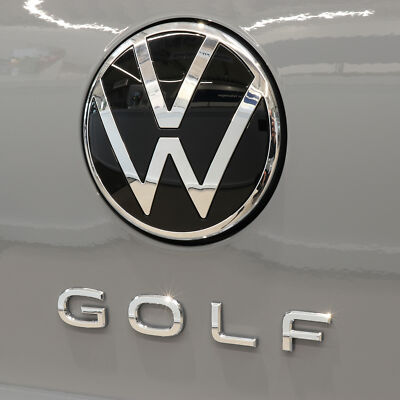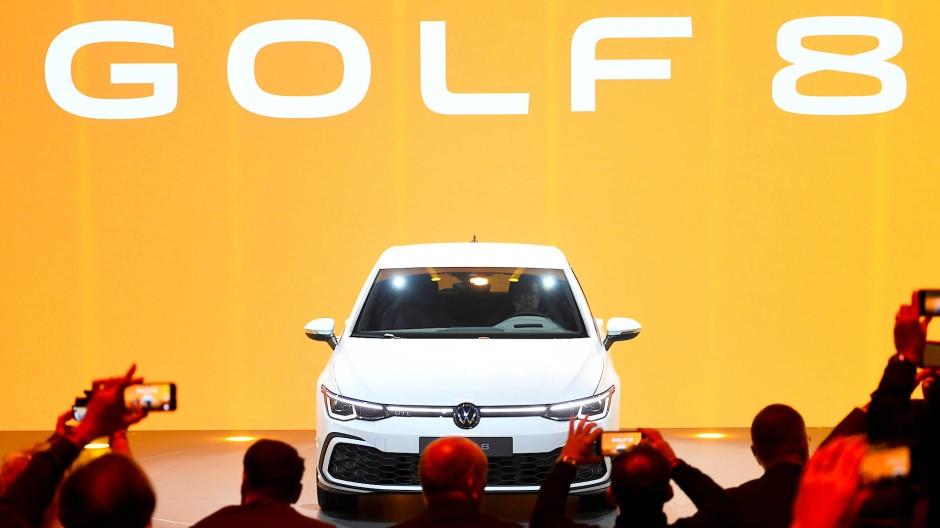
Suche Volkswagen Golf 8 Schriftart
ich bin auf der Suche nach der Schriftart des neuen Volkswagen Golf 8. Folgend ein Bild der Vorstellung.
Das entspricht dem Schriftzug auf dem Fahrzeug, dazu wird es – außer vielleicht für VW-interne Zwecke – keine Schriftart geben. Ob über diese vier Buchstaben hinaus eine komplette Schrift entwickelt wurde, glaube ich aber nicht. Wozu auch?
Es ist, gerade bei derart wertvollen Marken üblich, dass man bei einem Grafiker, oder sogar einem renonierten Schriftgestalter eine komplett neue, exklusive Schrift einzig für den imternen Gebrauch in Auftrag gibt, und eben nicht eine schon vorhandene Schriftart (die ja auch mal jemand entworfebn haben muss) verwendet wird, einfach, damit nicht irgendwo auf der Welt irgend ein Produkt schon diese Schrift nutzt, und es hier markenrechtliche Probleme geben könnte, bzw die Marke "GOLF" durch ein fragwürdiges oder anstößiges Produkt mit dieser Schrift geschädigt wird.
In diesem Fall denke ich jedoch, dass Volkswagen hier auch eine komplette Schrift, zumindest eine Versalien-Schrift in Auftrag gegeben hat, einfach um ein gleiches Schriftbild auch für weitere Fahrzeuge der Generation zu verwnden.
Das glaube ich nicht, es würden ja keine Abstände stimmen. Mag schon sein, dass weitere Buchstaben für verschiedene Logos entwickelt wurden, aber eine Schrift daraus generieren?
Da sehe ich eigentlich kein Problem, wenn diese Buchstaben  und eventuell Ziffern nur für den gleichen Zweck eingesetzt werden, und nicht um damit richtige Texte zu schreiben.